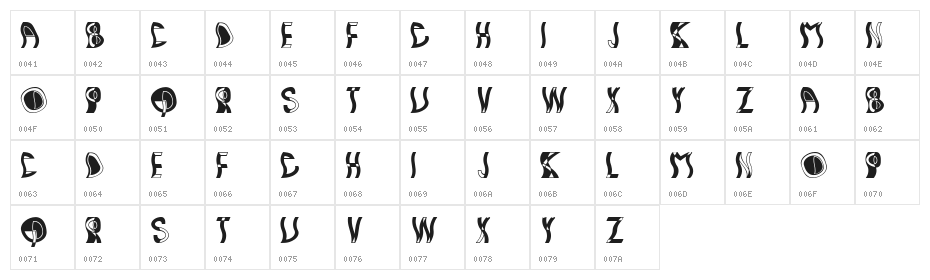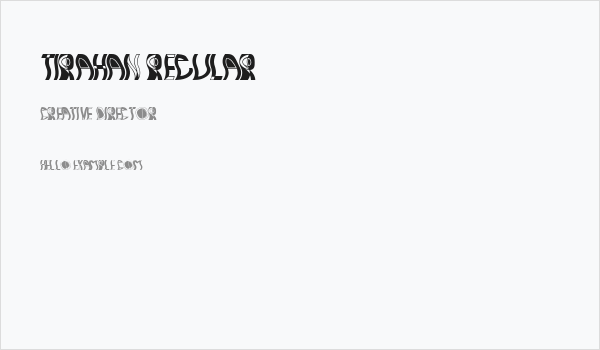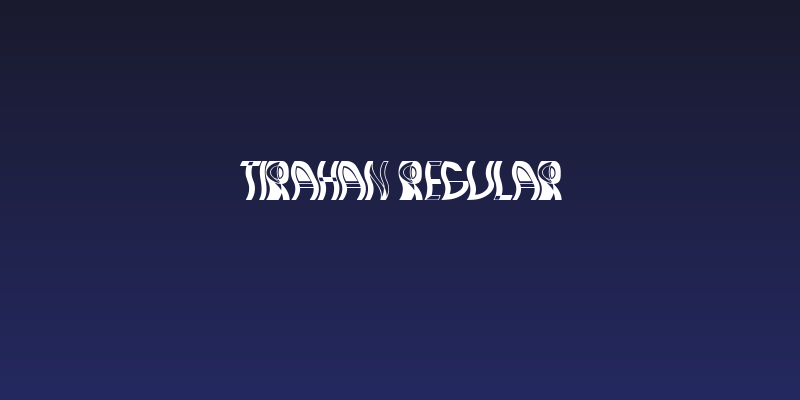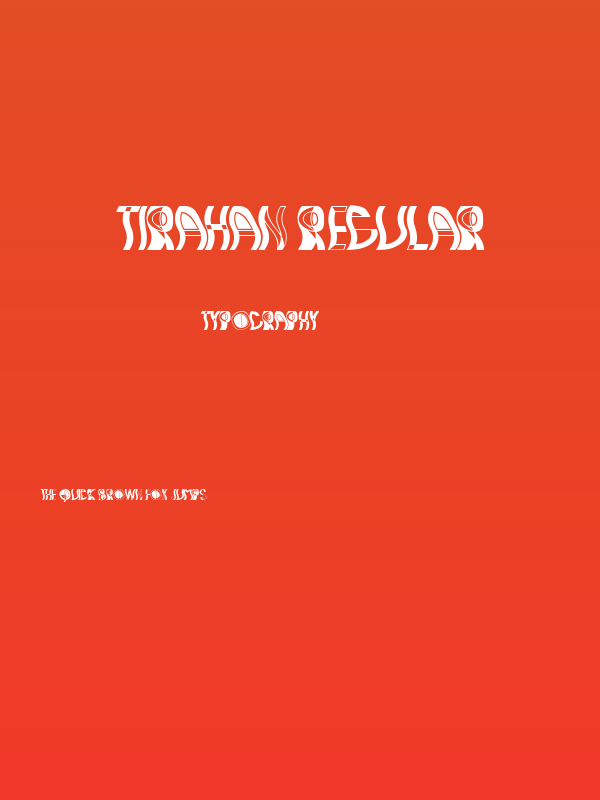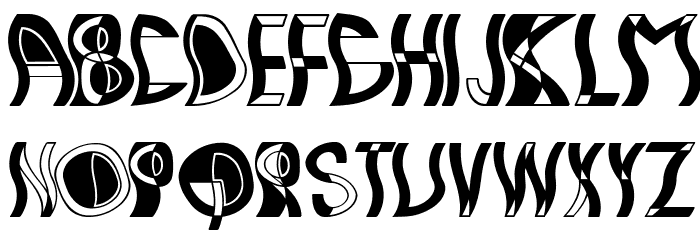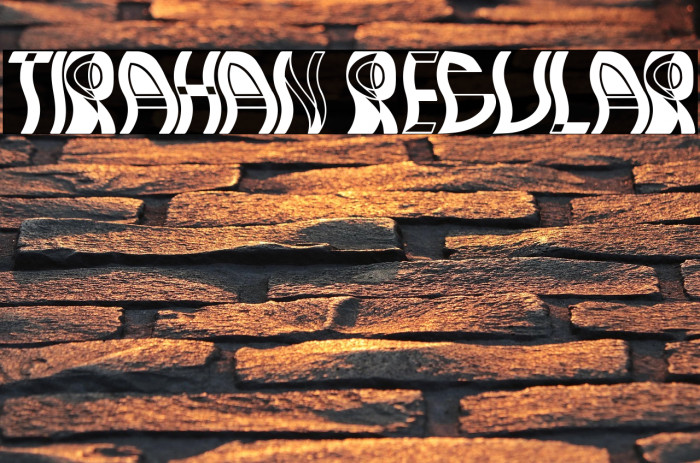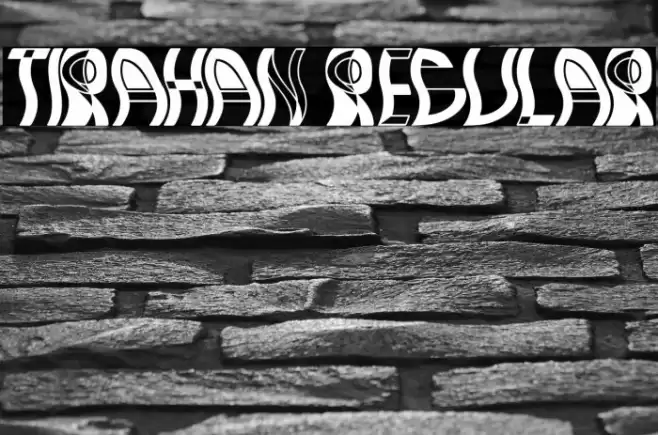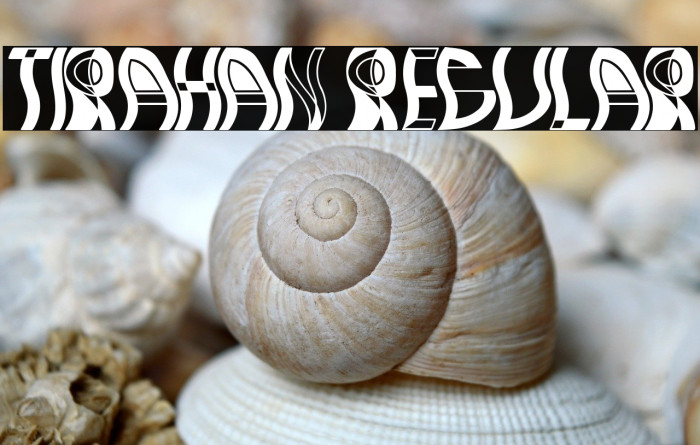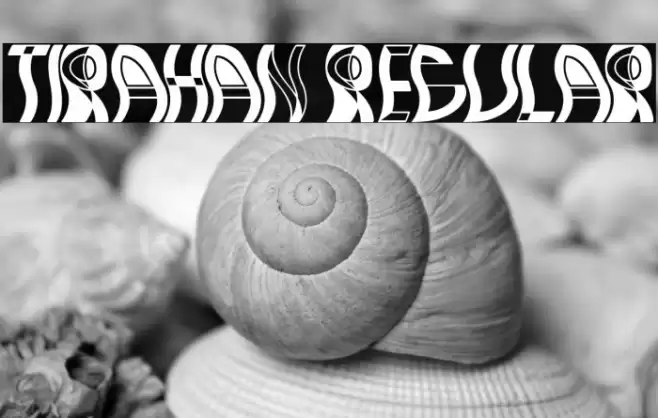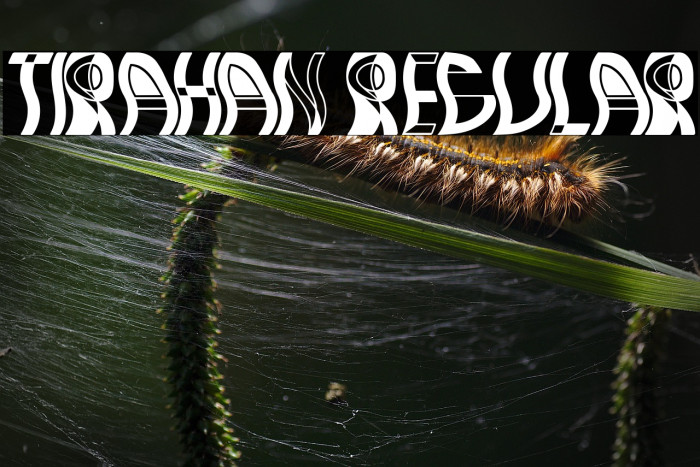
Tirahan Regular Font
✎ Distorted Eroded
| कंट्रास्ट | High |
| समग्र शैली | Modern, Avant-garde |
| उपयोग का मामला | Headlines, Logos, Artistic projects |
| सुझाए गए प्रोजेक्ट | Ideal for artistic posters, album covers, branding for creative industries, and any project seeking a bold, eye-catching typeface. |